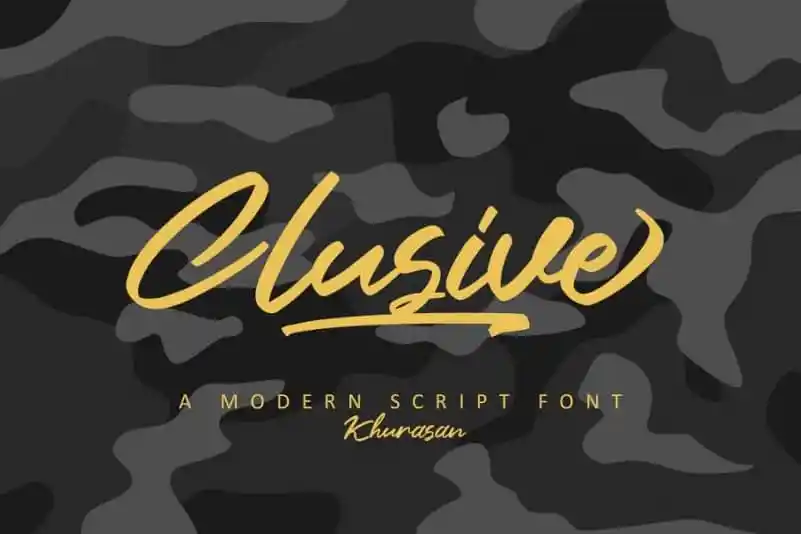
Clusive Handwritten Font – Download Grátis
A Clusive Handwritten Font é uma elegante tipografia de script que transmite naturalidade, sofisticação e perfeição para qualquer projeto extraordinário. Esta fonte foi criada pelo designer khurasan no site 99designs e mantém um estilo único e cheio de frescura, perfeitamente adequado a uma variedade de aplicações gráficas. Seja para os logotipos mais sofisticados ou as cartas de casamento requintadas, este tipoface é perfeito. Seus traços suaves e detalhes finos se destacam em tudo o que cria — desde identidades corporativas até cartões de visita e layouts. O Clusive Signature Typeface destaca-se também como uma escolha ideal para materiais de moda, convites de casamento, rótulos de produtos e outros elementos visuais. É um verdadeiro tesouro para quem busca personalidade em cada projeto gráfico que executa.